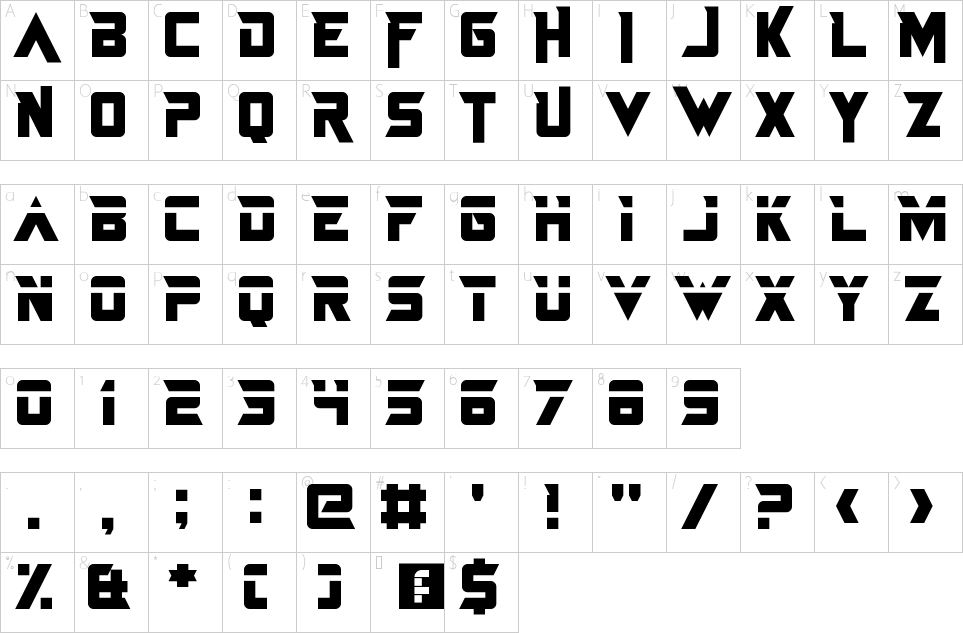
Just In The Firestorm Font | 1001 Free Fonts – Download Grátis
A fonte Just In The Firestorm é um elemento visual atraente disponível gratuitamente para Windows e Mac. Desenhada pelo designer Chequered Ink, esta fonte é uma escolha ideal para projetos que buscam um estilo distintivo e único. Embora não seja um design de fonte complexo, ela oferece um conjunto de letras uniformes que vão desde letras maiúsculas até minúsculas e pontos de interrogação. A fonte tem um estilo elegante e moderno que se destaca, ideal para ambientes de design que buscam um toque de personalidade e originalidade. Com seus downloads de mais de 7.237 vezes, Just In The Firestorm provou ser uma fonte versátil e altamente solicitada. Engane-se, esta fonte pode ajudar seu design a brilhar e fazer sua identidade visual se destacar.